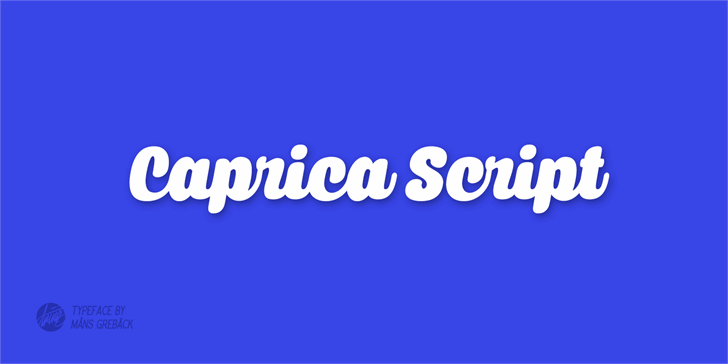
A ‘Caprica Script’ é uma fonte criada por Måns Grebäck em 2014 que oferece aos designers um estilo elegante e sofisticado para incorporar em suas criações digitais. Esta fonte vem com uma tipografia fluida e curvilínea, perfeita para criar um texto envolvente e chamativo em aplicativos de design gráfico como o Adobe Photoshop ou Illustrator. A ‘Caprica Script’ também é ideal para adicionar um toque único aos layouts web personalizados, tornando as páginas mais interessantes e atraentes. Aqui está uma fonte que combina com qualquer tipo de projeto digital – seja ele um site profissional, um layout de newsletter ou até mesmo um belo logotipo. Como Designer, você pode usar ‘Caprica Script’ para dar vida ao seu trabalho, tornando-o ainda mais personalizado e impecável. Ideal tanto para projetos pessoais quanto para uso em trabalhos profissionais, a fonte é perfeitamente adequada para aqueles que valorizam um visual elegante e sofisticado. Se você está procurando por uma fonte de script que se destaca com sua beleza fluida e curvilínea, ‘Caprica Script’ é certamente uma opção a considerar. Com seu design único, esta fonte será a escolha perfeita para aqueles que buscam um touch diferente em seus projetos digitais.